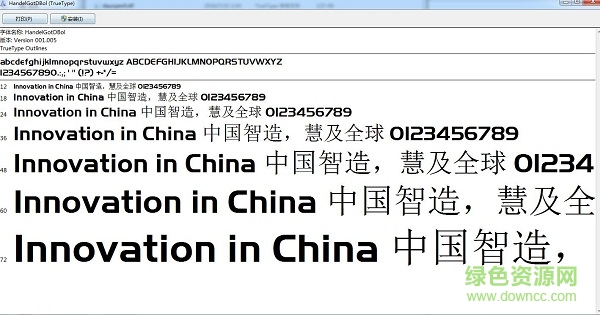
handelgotdbol是什么字體?handelgotdbol-普通(西方)是一款多用于屏幕顯示的無(wú)襯線字體,和灰度雅黑字體非常相似,字形扁方筆畫(huà)簡(jiǎn)潔,顯示效果非常清晰,歡迎大家免費(fèi)下載!
handelgotdbol字體非常的飽滿和優(yōu)美,支持高清顯示的ClearType功能,在同樣的字號(hào)下,單字面積就顯得更大,更容易識(shí)別,閱讀起來(lái)也更舒服。